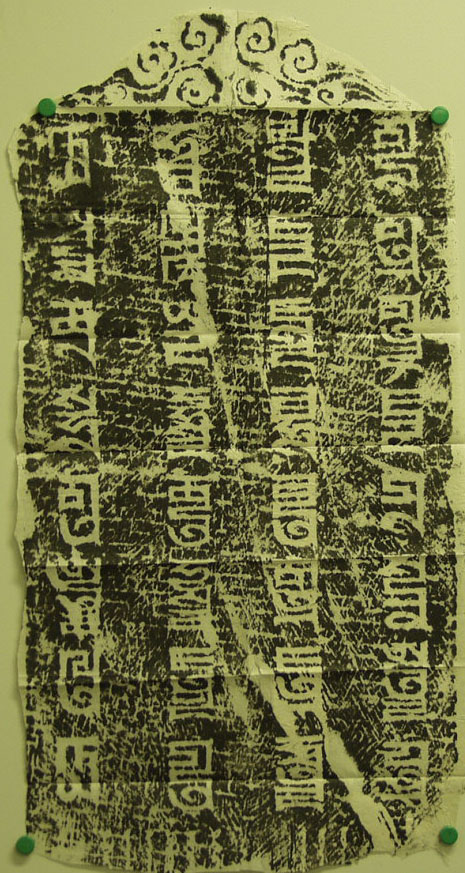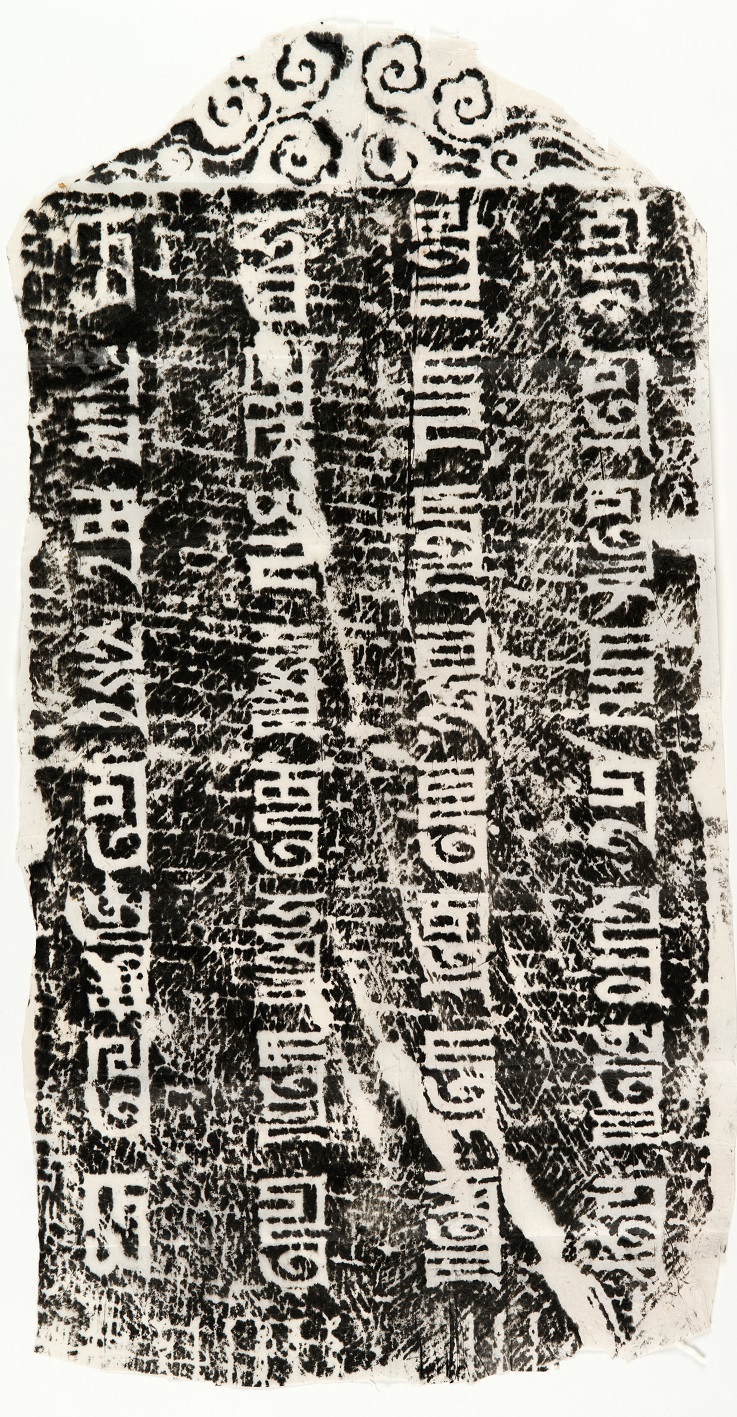
| 文字/言語 | パスパ文字/漢語 |
長田夏樹氏旧蔵拓本の一つ。元朝・元統3年(1335)の張氏先塋碑の碑額。張氏先塋碑には蒙古語面と
漢語面がある。この拓本は蒙古語面の碑額。碑額銘文はパスパ文字で書かれた漢語となっており、
左行より右行に読み進む。 1行目:t(a)y【大】-'ŭen【元】-č‘i【敕】-shi【賜】-gu【故】-'euŋ【榮】-lu【禄】-t(a)y【大】 2行目:fu【夫】-lėv【遼】-y(a)ŋ【陽】-dhiŋ【等】-č‘eu【處】-hĭiŋ【行】-ĵuŋ【中】-šeu【書】 3行目:piŋ【平】-ĵ(a)ŋ【章】-ĵiŋ【政】-čhi【事】-čeu【柱】-guė【國】-ĵuė【追】-fuŋ【封】 4行目:gei【薊】-guė【國】-guŋ【公】-ĵ(a)ŋ【張】-ši【氏】-sen【先】-'euŋ【塋】-buė【碑】 とあり、「大元敕賜故榮禄大夫遼陽等処行中書平章政事柱國追封薊國公張氏先塋碑」となる。 なお、【塋】は y1euŋとすべきところ'euŋとある。 (文責:吉池孝一2012.6.19) *新たに撮影した画像を追加しました。(2015.1.7) 同碑の碑身蒙古語面はpuz2p02、碑身漢語面はpuz2p04、 碑額部分(漢字篆書体)はpuz2p03を参照。 |